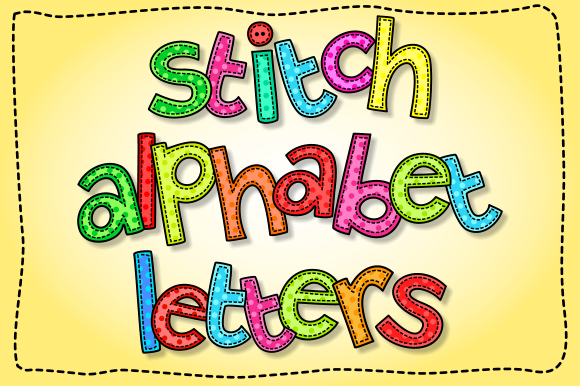
Lowercase Stitch Alphabet Clipart
Ulasan Lengkap: Lowercase Stitch Alphabet Clipart
Se você está procurando uma fonte de letras criativas e totalmente hand‑drawn para seus projetos de artesanato, o Lowercase Stitch Alphabet Clipart chega como a solução perfeita. Este pacote traz 26 letras minúsculas com um estilo costurado único, ideal para convites, scrapbooks, estampas de camisetas e muito mais.
- Estilo exclusivo: Cada letra parece costurada à mão, oferecendo um toque artesanal que se destaca em qualquer projeto.
Além de entregar arquivos de alta resolução, o Lowercase Stitch Alphabet Clipart oferece um design exclusivo que não se encontra em bancos de imagens genéricos. Isso significa que seus projetos terão identidade própria, aumentando o valor percebido pelos seus clientes ou convidados.